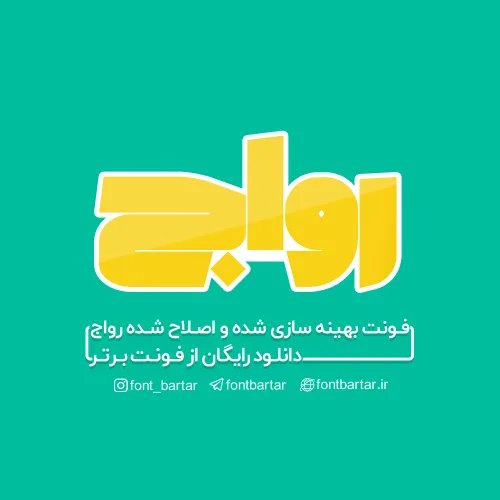
فونت فارسی رواج
فونت رواج
فونت فارسی رواج
دانلود فونت گرافیکی رواج ، فونت فوق العاده زیبا مناسب تایپوگرافی ، آماده سازی شده در سه سبک که بصورت رایگان از فونت برتر ارائه می گردد،ساختار این فونت زیبا مدرن و در مقابل دارای المان هایی سنتی است که همین ویژگی این فونت را خاص و جذاب کرده است،این فونت را می توان برای عنوان و یا طراحی تایپوگرافی ، لوگو استفاده کرد همچنین این فونت بسیار کمیاب می باشد و نسخه فاینال و اصلاح شده فونت فارسی رواج هم اکنون از فونت برتر در دسترس می باشد،این فونت را به لحاظ ساختار می توان در نوع فونت های فانتزی و گرافیکی قرار داد.